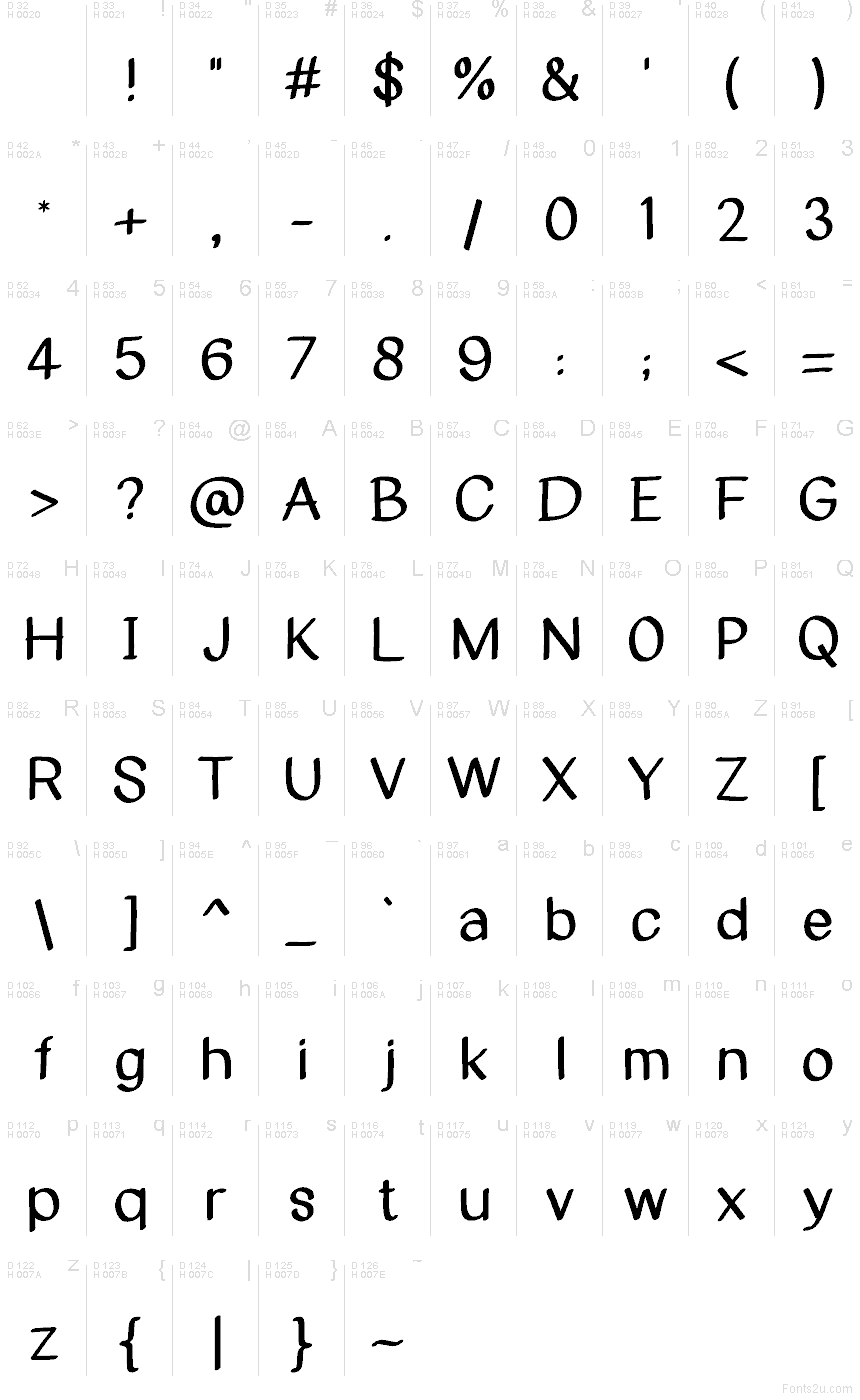
Pertamax fake
La police Pertamax Fake, créée par Hello Good Studio, est une écriture manuscrite gratuite aux formes arrondies et décontractées, dotée de courbes fluides et harmonieuses. Son dessin conserve le rythme naturel d'une écriture à la main, avec des formes ouvertes et des jointures douces qui confèrent au design une atmosphère conviviale et authentique.
Pertamax Fake s'adapte parfaitement aux citations, invitations, logos, packagings, visuels pour réseaux sociaux et aux textes courts d'affiches, car sa structure manuscrite inspire la proximité. Cette police gratuite est également idéale pour les cartes de vœux et les étiquettes lorsque vous recherchez un rendu qui semble avoir été écrit à la main plutôt que composé mécaniquement.